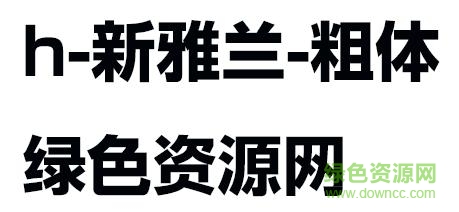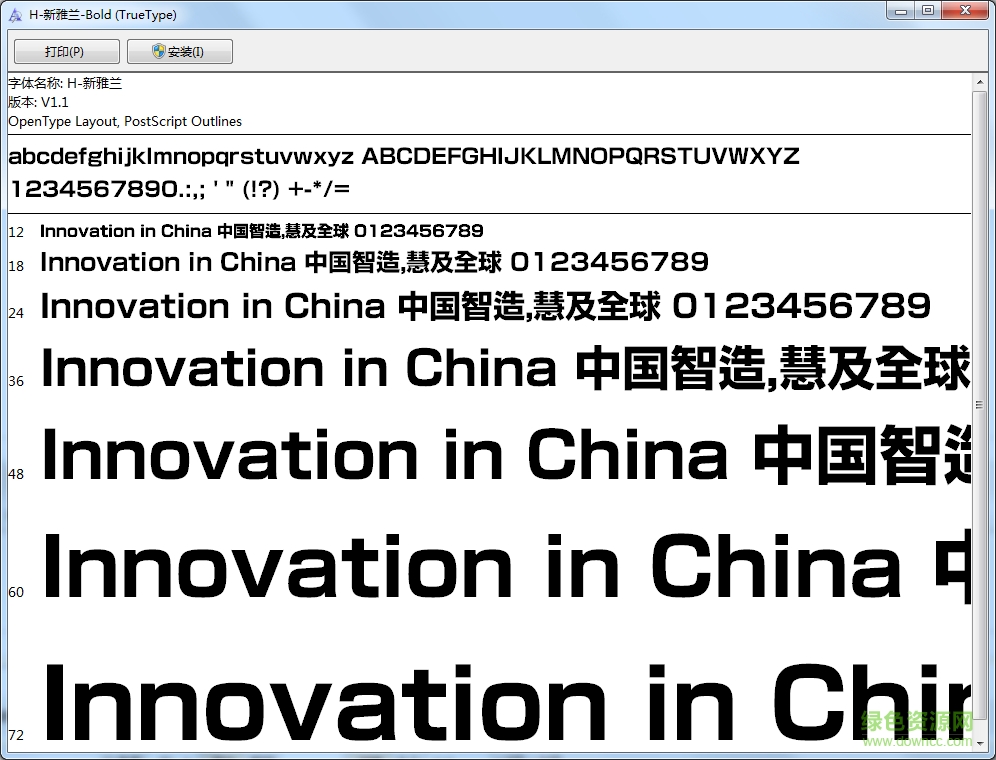
h 新雅蘭 bold字體是一款美觀大方的中文粗體字體,特征鮮明,清晰度高,具有醒目和便于閱讀的優(yōu)點(diǎn),適用范圍廣,歡迎大家在綠色資源網(wǎng)免費(fèi)下載新雅蘭粗體ttc字體!
廣泛應(yīng)用于黑板報(bào)、企業(yè)名稱、會(huì)場(chǎng)布置、展覽會(huì)、宣傳、廣告、商標(biāo)、標(biāo)語(yǔ), 以及各類廣告、商品包裝和裝潢、報(bào)刊雜志和書(shū)籍的裝帖上等!